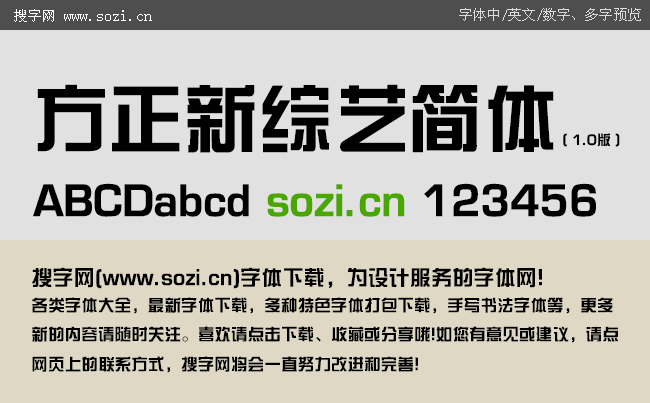
方正新綜藝簡體
搜字網(wǎng)提供一款方正新綜藝簡體字體下載。綜藝體是黑體的一種變體,也是藝術(shù)字的一種。特點(diǎn)是筆劃更粗,盡量將空間充滿。同時為了美觀,對拐彎處的處理較為圓潤。此款綜藝體粗細(xì)適中,適用于廣告、報刊等的標(biāo)題及海報展板等設(shè)計(jì)場合使用。